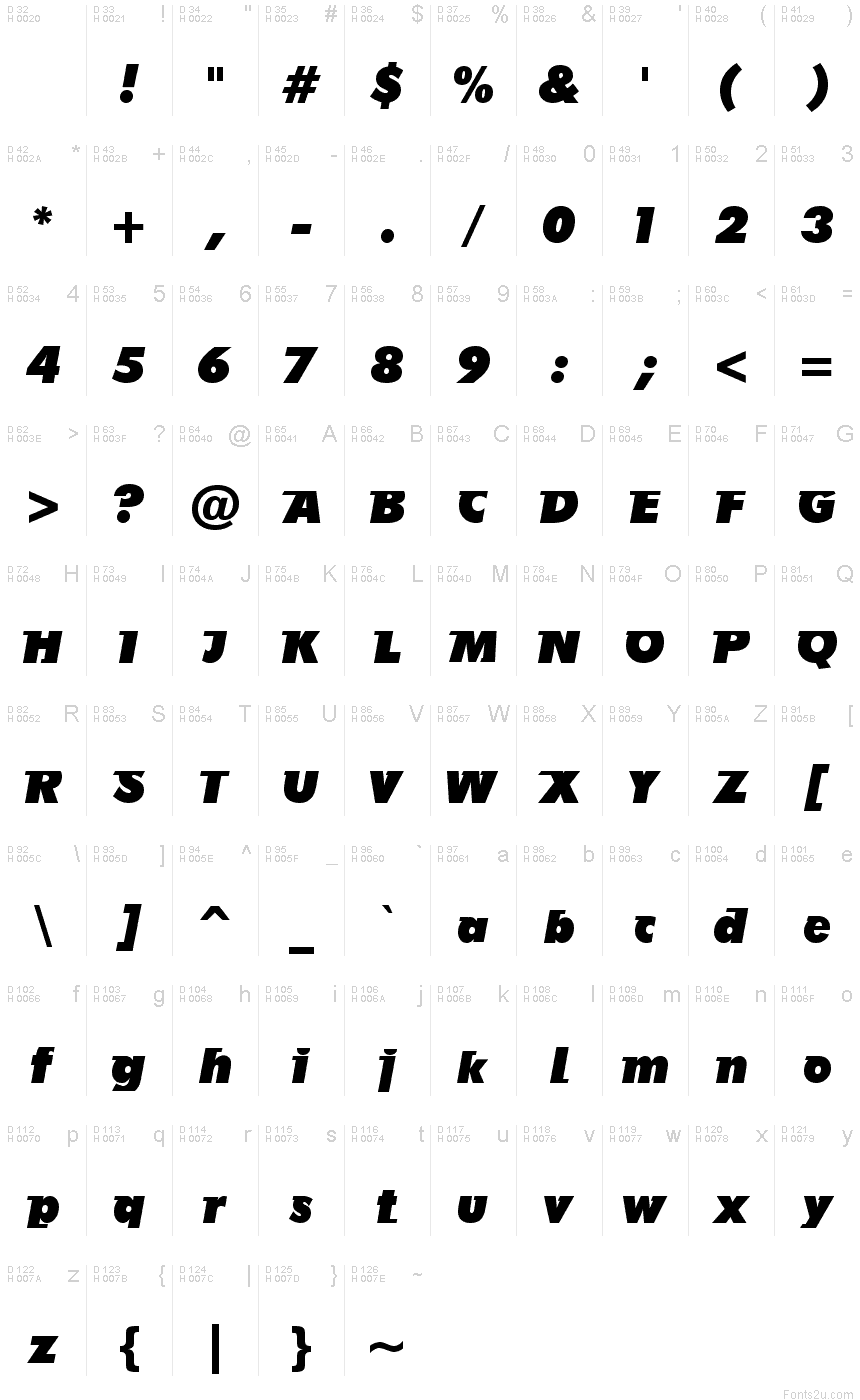
AB Futurun autorstwa Amita Botre to bezpłatny, gruby i pochyły krój display, zbudowany z szerokich, ciasno spasowanych liter o mocnym pochyleniu w przód i powiększonych geometrycznych formach. Ścięte zakończenia i zwarte światła wewnętrzne nadają mu techniczną dynamikę.
Kanciaste grafiki pojazdów i opływowe motywy produktowe doskonale współgrają z jego dynamiczną sylwetką, dzięki czemu krój sprawdza się na plakatach poświęconych sportom motorowym, w brandingu sportowym, na opakowaniach produktów technologicznych oraz w grafice futurystycznych gier arcade. Najbardziej przekonująco prezentuje się jako logo zespołu wyścigowego, gdzie gęste formy przypominają indywidualne liternictwo namalowane bezpośrednio na maszynie i stają się integralną częścią wizerunku samego pojazdu.